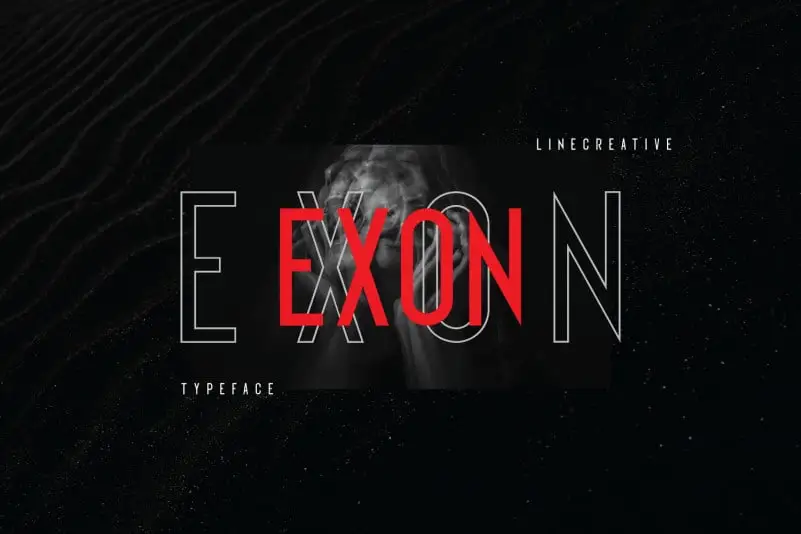
Exon Sans Serif Font – Fonte Grátis
Exon Sans Serif Font
Exon Sans Serif Font é uma elegante fonte de exibição para quem busca simplicidade e charme. Ideal tanto para design gráfico quanto para criação de headlines, esta fonte transmite um ar de limpeza e sofisticação incomparável. Ela se destaca especialmente como título ou em outros elementos visuais que necessitam de destaque. A Exon vem em duas variações: Regular e Outline. Esta característica permite personalizar ainda mais a aparência da fonte para atender aos diferentes propósitos e estilos, seja eletrizante ou discreto, de acordo com o design em questão. Sua simplicidade não diminui sua elegância, ao contrário, ela destaca-se como uma opção perfeita para qualquer situação que exige beleza e confiabilidade. Com Exon Sans Serif Font, a complexidade da forma torna-se algo simplesmente belo, o que torna esta fonte um excelente recurso para quem deseja transmitir elegância e sofisticação em seus projetos visuais.